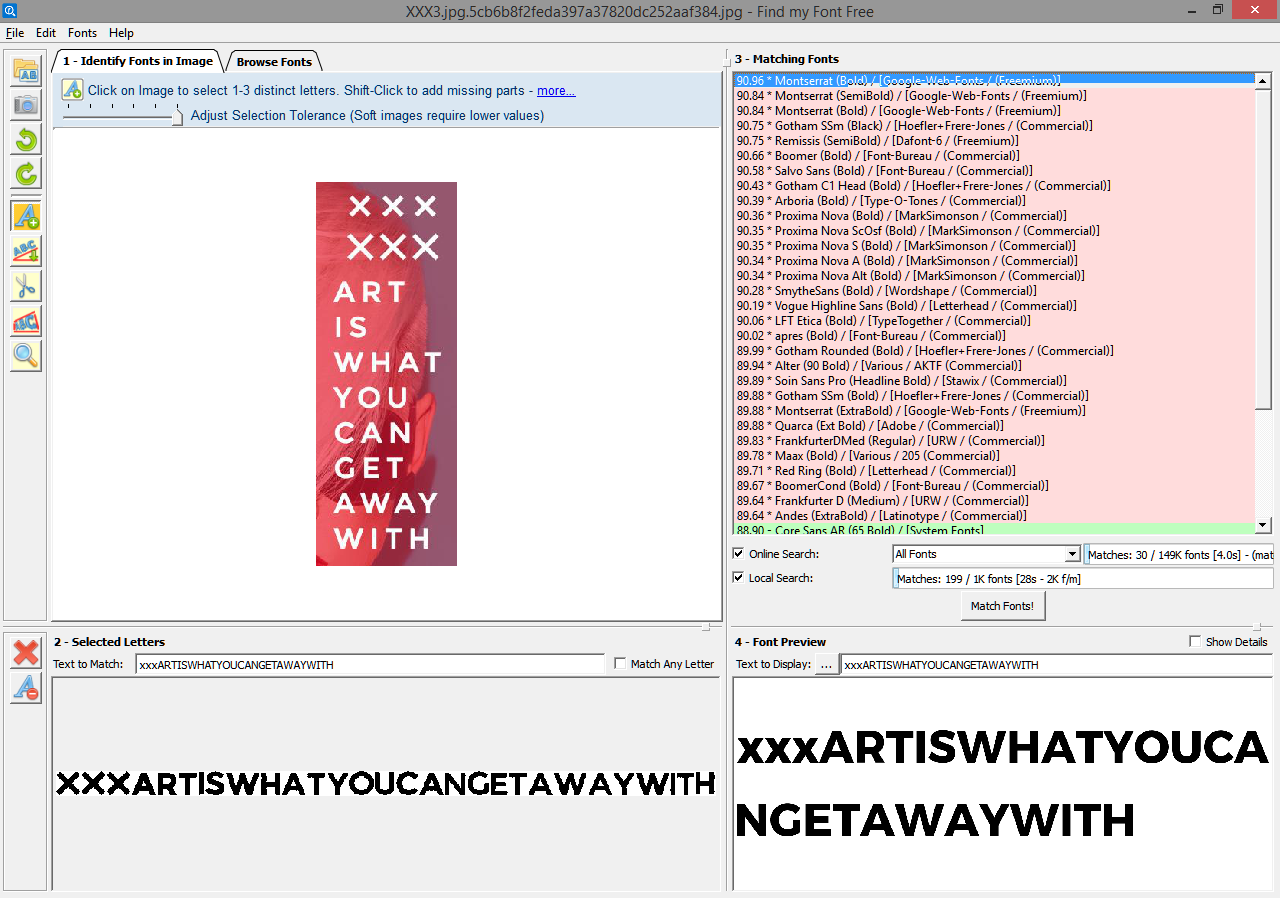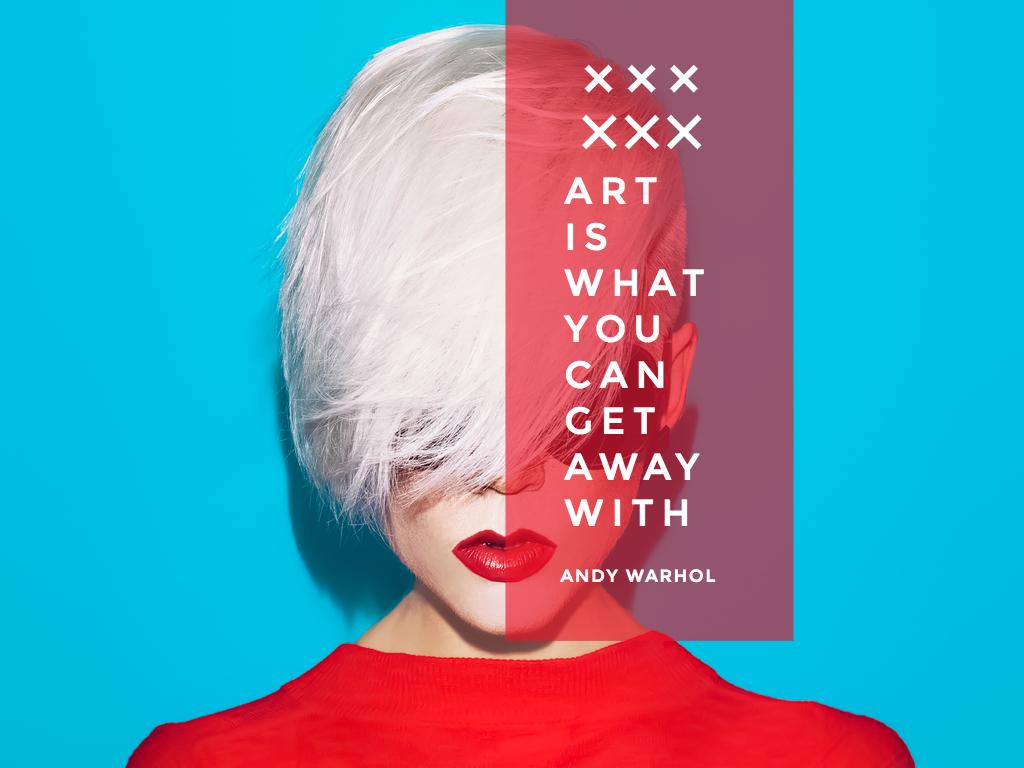
Schrift auf shutterstock-Foto gesucht
Ich suche diese Schrift, von der ich leider nicht mehr habe als dieses Musterfoto von der shutterstock-Webseite / aus einem shutterstock-Newsletter.
Trotz eindeutigem »X« und »G« bin ich bei den Klassikern nicht weitergekommen…
Sicher, dass dies das /X ist? Ich hätte auf das Multiplikationszeichen /× getippt.
In die Richtung des Beispiels geht schon mal die »Montserrat« von Julieta Ulanovsky (2011) – ist gratis bei Fontsquirrel oder Google Fonts verfügbar (https://www.fontsquirrel.com/fonts/montserrat). In der Montserrat ist das /S allerdings breiter und offener und das /G hat etwas mehr »Überbiss«, soweit ich das im Vergleich mit der Grafik beurteilen kann. [Nachtrag: Die hat @bertel ja schon einen Moment früher vorgeschlagen]
Bei den kostenpflichtigen Fonts könnte die »Trenda« ganz gut hinhauen (Daniel Hernández und Paula Nazal Selaive für Latinotype, 2016). Hier wirken in der OP-Grafik aber z. B. das /C etwas geschlossener und der Anstrich beim linken /N-Schenkel breiter.
Die ist es sogar ganz sicher. Das Bild stammt wie gesagt von shutterstock, dort kann es im dortigen Online-Editor bearbeitet werden. Der Doppelklick auf die Schrift, um sie zu bearbeiten, zeigt, dass die Montserrat verwendet wurde.
Man kann die einzelnen Striche im Online-Editor verschieben :-) …